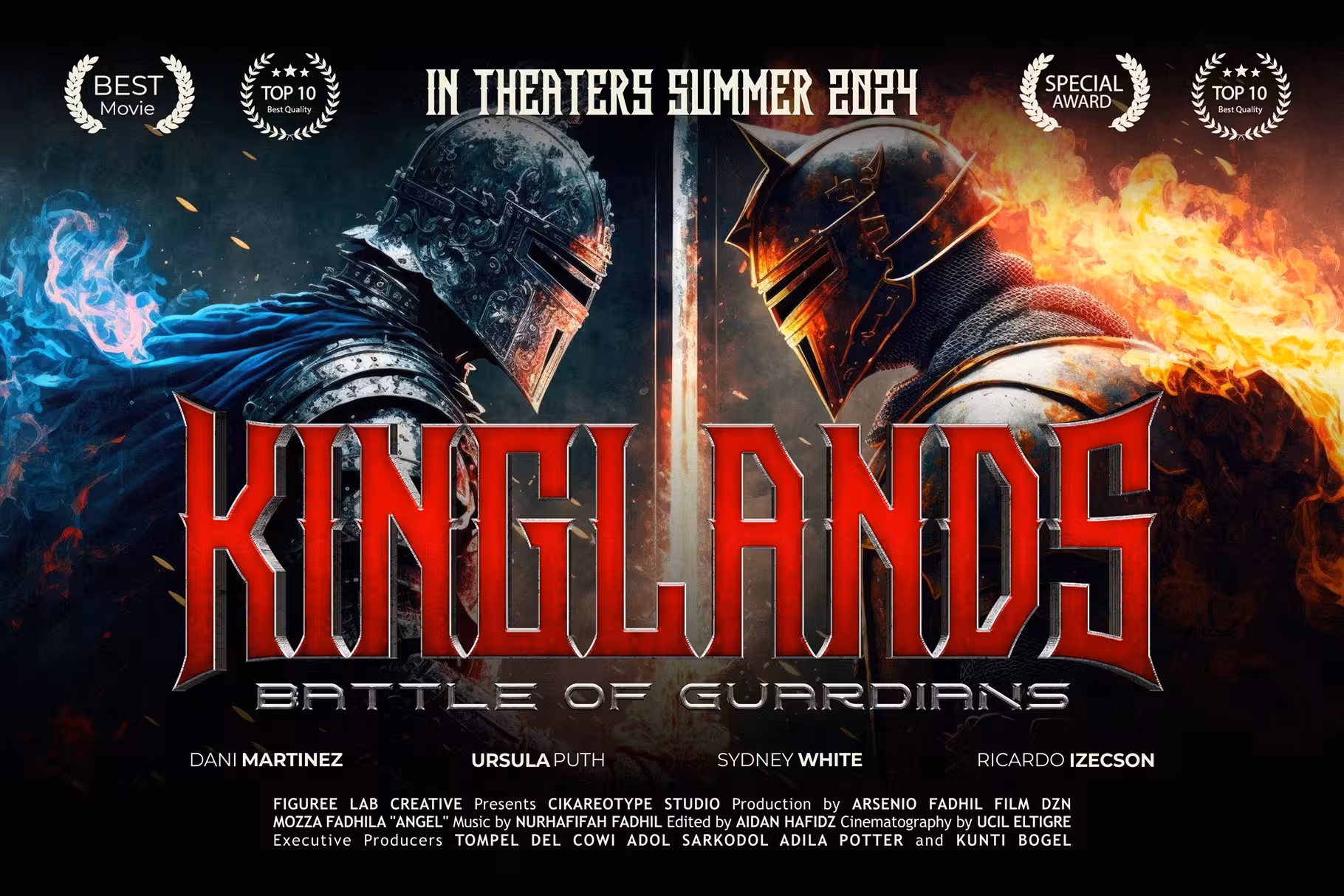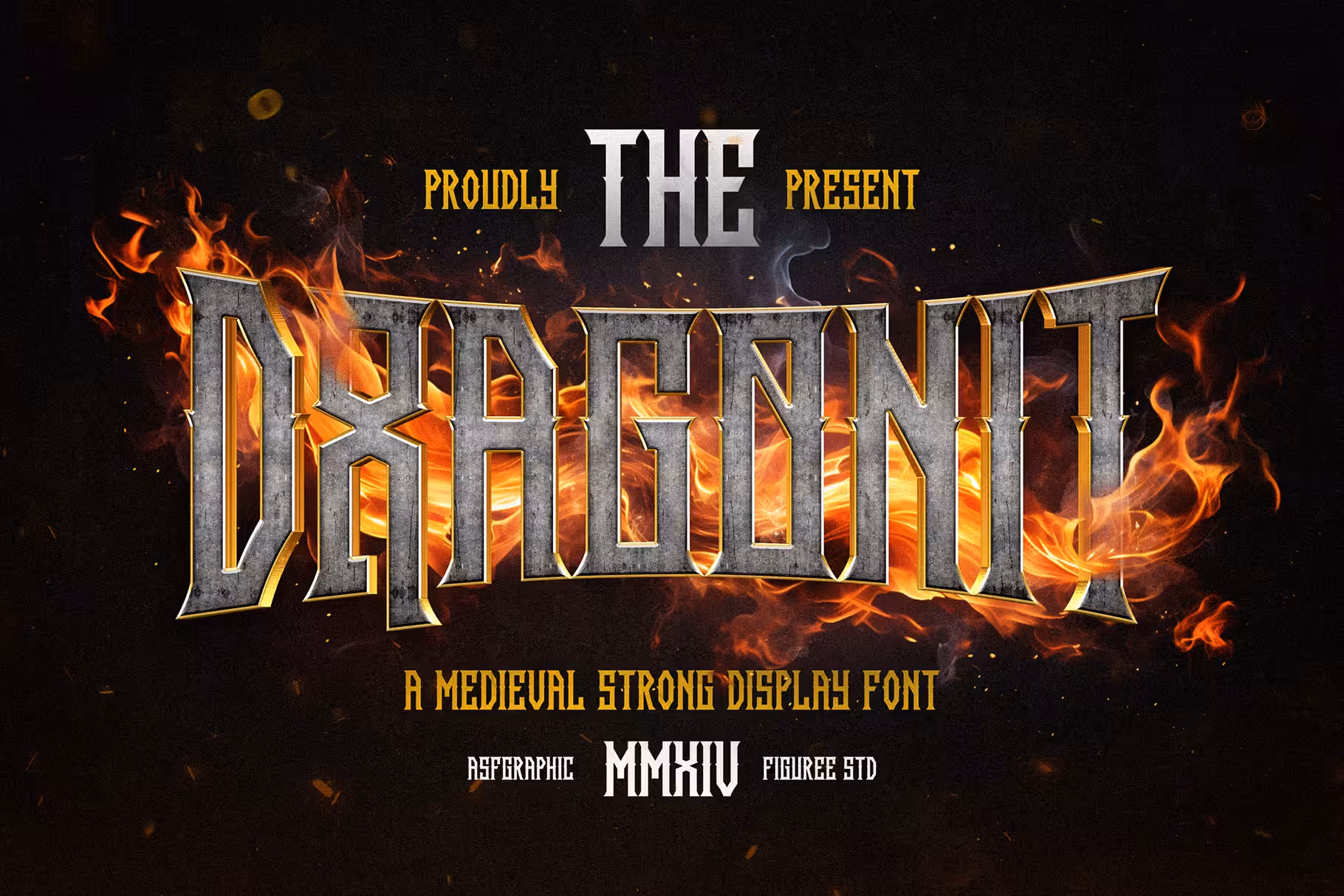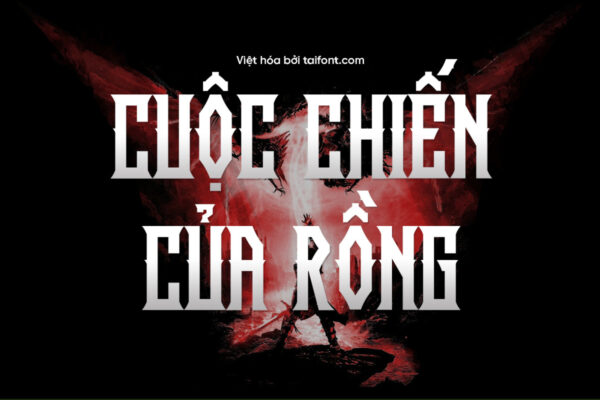
Giới thiệu về Font TF Dragonit Việt hóa
TF Dragonit Việt hóa là một font chữ trang trí nổi bật với thiết kế mạnh mẽ, sắc nét và đầy kịch tính, gợi cảm giác về những trận chiến sử thi, thế giới giả tưởng và những câu chuyện về rồng. Font này toát lên vẻ oai phong, bí ẩn và đầy quyền lực, lý tưởng để tạo điểm nhấn độc đáo và thu hút mọi ánh nhìn, đặc biệt trong các thiết kế liên quan đến game.
Với đặc điểm thiết kế độc đáo, đường nét dứt khoát và khả năng gợi cảm xúc mạnh mẽ về sự chiến đấu, Dragonit là lựa chọn hoàn hảo cho các ấn phẩm trong lĩnh vực giải trí, đặc biệt là poster game:
- Thiết kế Poster Game: Hoàn hảo để tạo các tiêu đề chính (headline), slogan, hoặc thông điệp quảng cáo trên poster, banner, hoặc bất kỳ ấn phẩm nào cần sự chú ý tối đa. Nét chữ mạnh mẽ của font giúp thông điệp của bạn nổi bật, dễ đọc và truyền tải một cách hiệu quả ngay từ cái nhìn đầu tiên.
- Thiết kế Game: Lý tưởng cho logo game, tiêu đề, hoặc các yếu tố giao diện người dùng (UI) trong game có chủ đề giả tưởng, thần thoại, hoặc các trò chơi phiêu lưu. Nét chữ sắc sảo của font sẽ làm tăng tính chân thực và độ “ngầu” cho trò chơi.
- Thiết kế poster và banner: Phù hợp để tạo các tiêu đề chính, slogan, hoặc thông điệp quảng cáo trên poster, banner cho các sự kiện công nghệ, hội thảo, hoặc các sản phẩm muốn gây ấn tượng thị giác mạnh mẽ.
- Thiết kế nhận diện thương hiệu: Có thể dùng cho logo hoặc bộ nhận diện thương hiệu của các công ty, doanh nghiệp trong lĩnh vực gaming, giải trí, hoặc các sản phẩm mang tính đột phá và hướng tới tương lai.
Với TF Dragonit Việt hóa, bạn có thể dễ dàng thổi hồn mạnh mẽ, sự độc đáo và cá tính vào các thiết kế, tạo ra những sản phẩm không chỉ đẹp mắt mà còn cực kỳ ấn tượng và có khả năng thu hút sự chú ý tối đa.